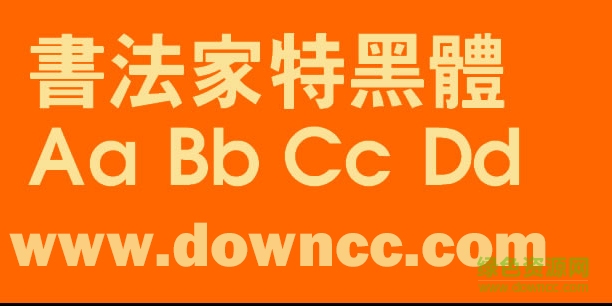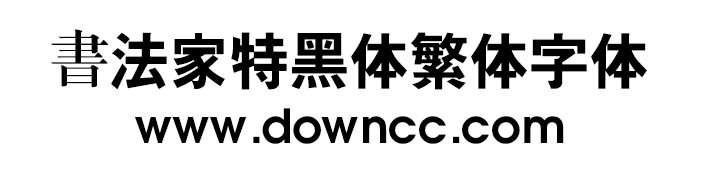
書法家特黑體繁體是一款非常典雅的繁體字,字體線條蒼勁有力,字形優(yōu)美大方,喜歡這款字體的朋友歡迎在綠色資源網(wǎng)下載!
黑體因它字體較粗,橫豎粗細(xì)一致,方頭方尾,點(diǎn)、撇、捺、挑、勾也都是方的,所以又叫方體,在這里結(jié)合了繁體的字形,所以可以想象這款字體特別受歡迎。